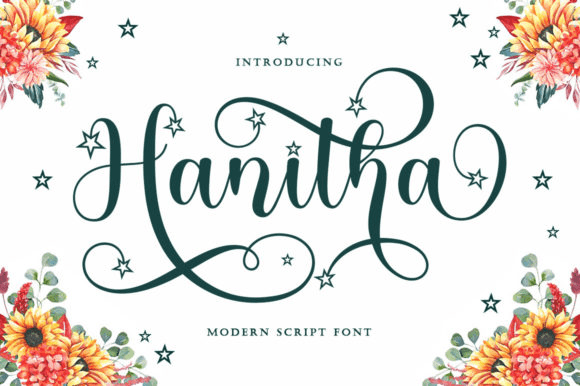
Название: Hanitha Font
Hanitha - это нежный и милый каллиграфический шрифт с символами, которые танцуют вдоль базовой линии.
Он добавит роскошную искру в любой дизайнерский проект, который вы хотите создать!
Название: Hanitha Font
Hanitha - это нежный и милый каллиграфический шрифт с символами, которые танцуют вдоль базовой линии.
Он добавит роскошную искру в любой дизайнерский проект, который вы хотите создать!